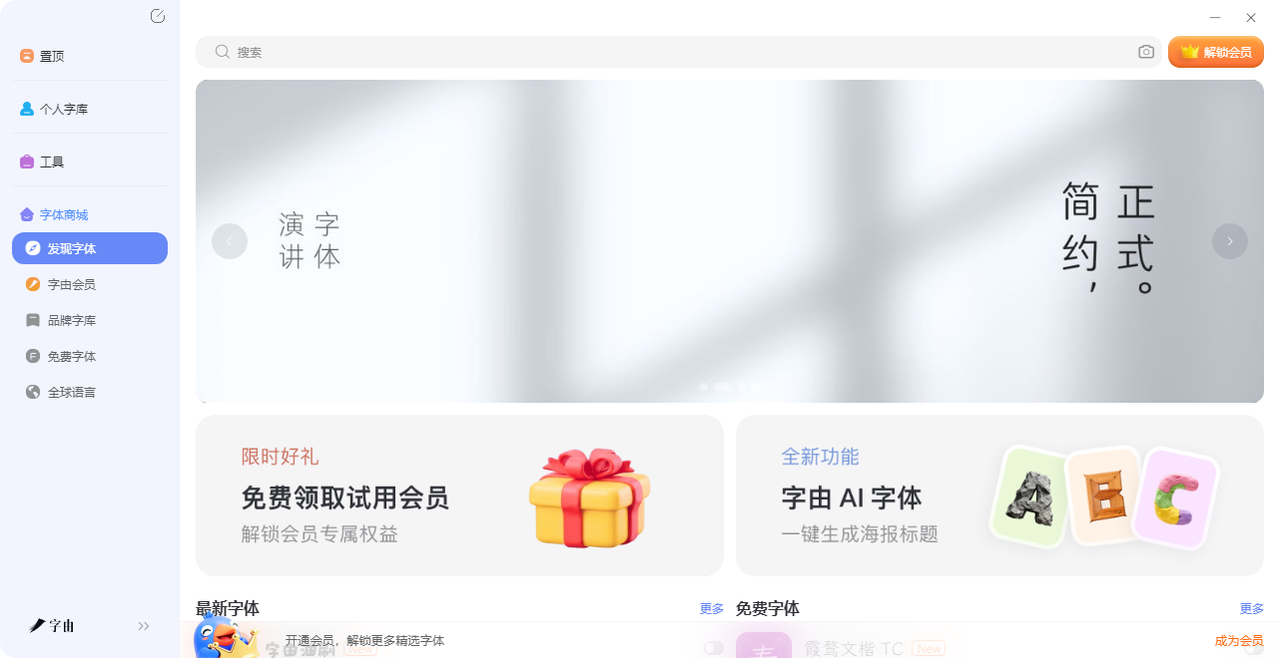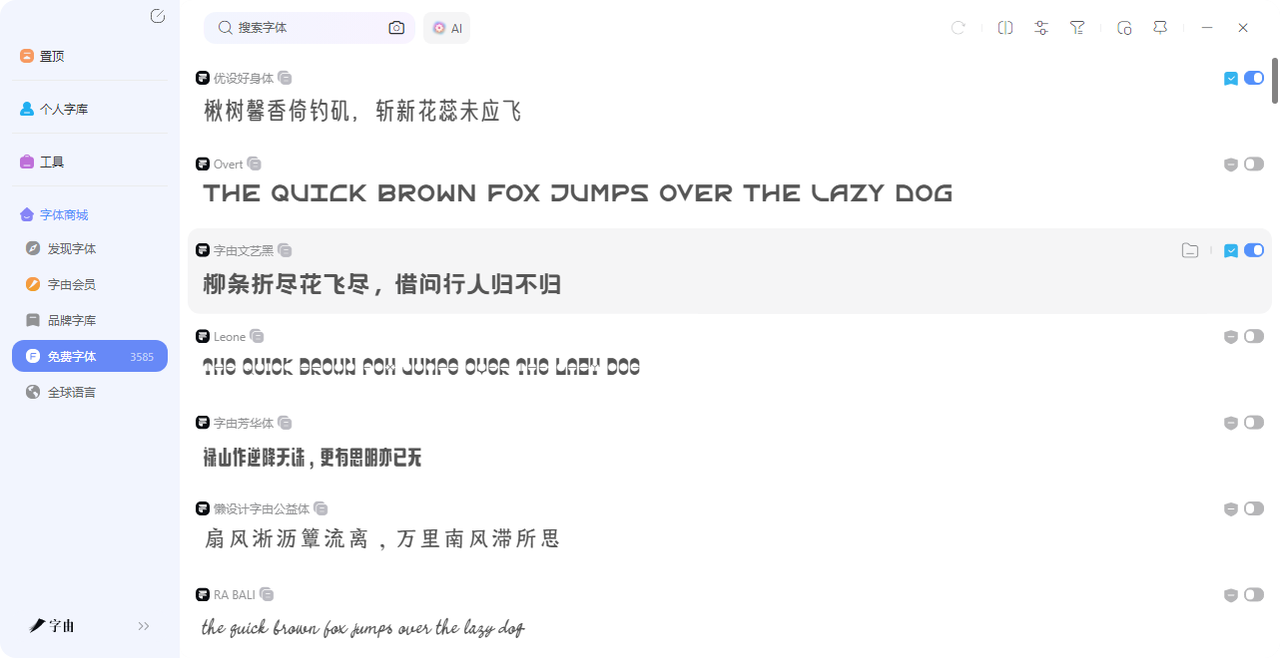
字体大师实测:字由的免费商用字体库和AI工具到底有多强?
如果说你在做设计,但是还没有听说过或者是还没有用到过字由,那简直是亏大了。它不仅是一个字体工具,不用下载安装字体文件,点一下就能直接在PS和Word里用,而且库里目前还有3000多款免费商用字体,还带了AI识字、AI字体生成这些非常实用的功能,完全能称得上“字体大师”,今天我会挨个把字由好用的地方都给你讲讲。
字由(hellofont.cn)是一个集字体库、字体管理、AI工具于一体的平台。隶属于上海驿创信息技术有限公司,2015年创立,核心口号是“让用户用字更自由”。目前聚集了超千万设计师、创意人才、运营人员等用户。
它有网页版和客户端两种形态。网页版可以浏览和预览字体,但要想真正把字体用到PS、AI里,得下载客户端。客户端才能实现“一键应用到设计软件”。
2、免费字体库
这是字由最核心的价值。关于免费商用字体的数量,不同渠道的数据略有差异,但都在一个量级。
官方在2026年初的版本更新中提到,平台收录了10500多款字体,其中免费商用字体已增加到3585款。这个体量在国内同类平台中属于第一梯队。更重要的是,这些字体都有第三方厂商的正版授权。每一款在详情页都会明确标注授权类型和商业使用权限,从源头降低版权风险。
具体到字体,热门的有这些:中文字体方面,黑体类有思源黑体、阿里巴巴普惠体、优设标题黑、字由文艺黑、鸿蒙黑体、钉钉进步体、站酷酷黑等;宋体类有思源宋体、思印宋等;楷体类有阿里妈妈东方楷体、江西拙楷等。英文免费商用字体则包括Playfair Display、Oswald Medium、Hanchan Serif、Poppins Bold等。其他热门款还有优设好身体、阿里妈妈东方大楷、抖音美好体等,全部支持免费商用。
3、实用AI工具
字由不是只有字体库。它内置了好几款AI工具,覆盖了字体识别、生成、配字等场景。
AI识字:上传图片,3-5秒识别字体
这功能解决了一个特别实际的痛点——看到一张海报上的字体很喜欢,但不知道叫什么。操作很简单:打开字由客户端或官网,进入「AI识字」功能页,把图片拖进去,系统3-5秒内自动分析并识别文字区域。然后返回匹配的字体结果,同时标注是否为免费商用字体及授权类型。如果你在PS或Figma里设计,可以直接点击激活字体,然后在软件里立即使用。
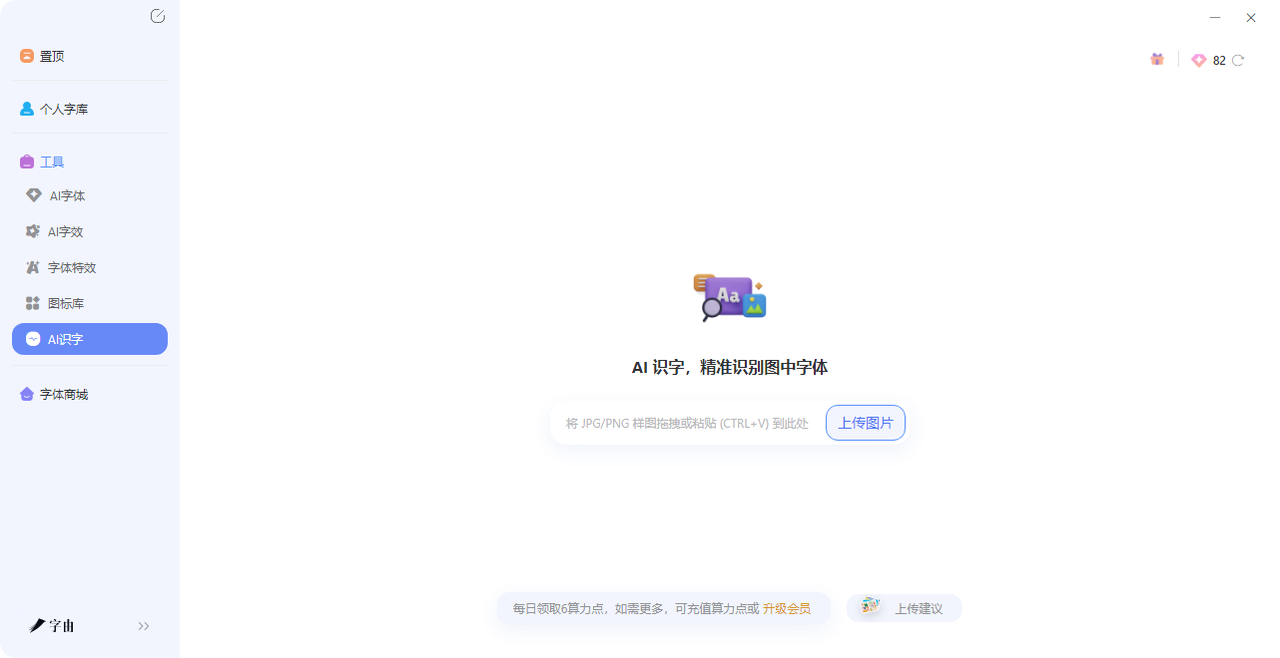
字由5.0版本还进一步升级了这项功能:AI会在识别后同步匹配库内的官方授权信息与商业使用权限,并提供相似字型选项。也就是说,哪怕识别出来的字体不在字由库里,系统也会给你推荐长得像的替代品。
AI字体:输入文字,选模板,几十秒生成艺术字图片
这功能适合不会PS又想出艺术字效果的人。操作分三步:打开字由的AI字体功能页,选模板(电商促销、国风、涂鸦、科技感等风格全覆盖),点“做同款”,输入想做的文字(比如“开业大吉”“春日上新”),点生成。生成时间大约6-7秒,和模板风格一致,笔画比例规整。生成后可以下载透明背景的PNG图,拖进海报直接用。
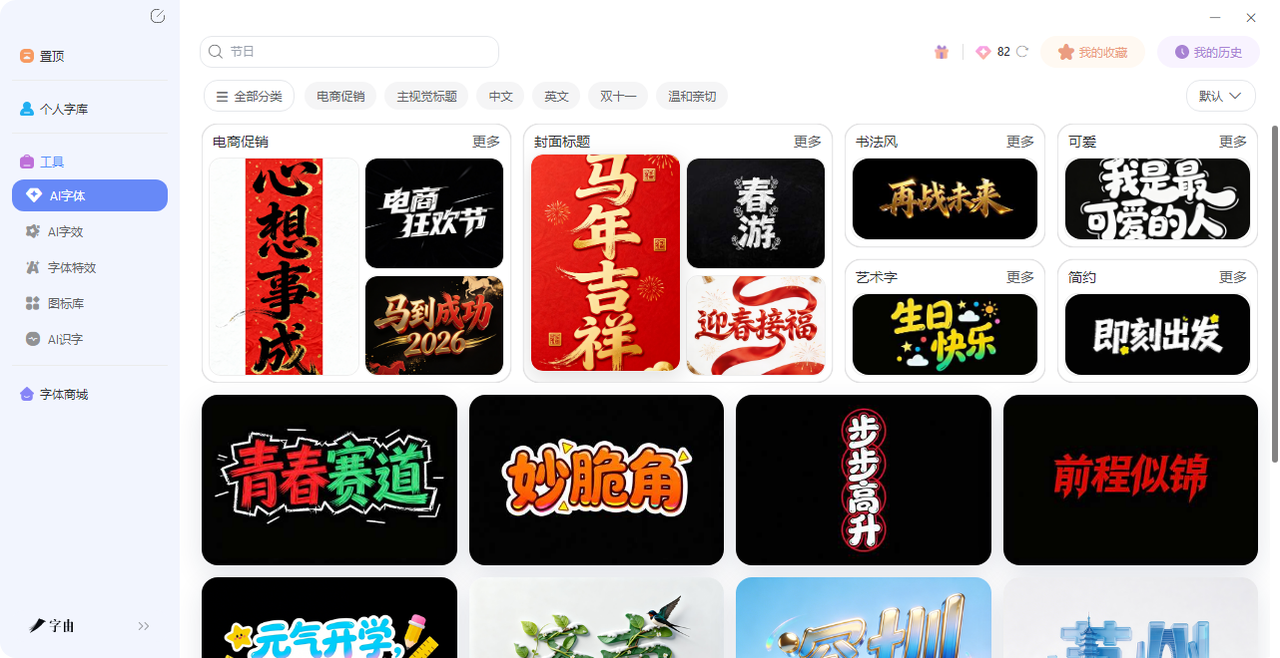
字由AI字体的定位是“将复杂留给自己,将简单留给用户”,通过预制高质量字体模板实现“输入即所得”。在4款国产AI字体工具的横向测评中,它在稳定性和易用性上表现最佳。缺点是完全不懂AI的新手也能顺畅使用,能保证质量。缺点是自定义自由度较低。
AI擦除:去水印修图,几秒搞定
上传一张带文字的图片,AI智能识别图中所有文字,你想去掉哪句就选哪句,擦除后背景自动修复,看不出痕迹。做海报去水印、改文案修图,几秒钟搞定。
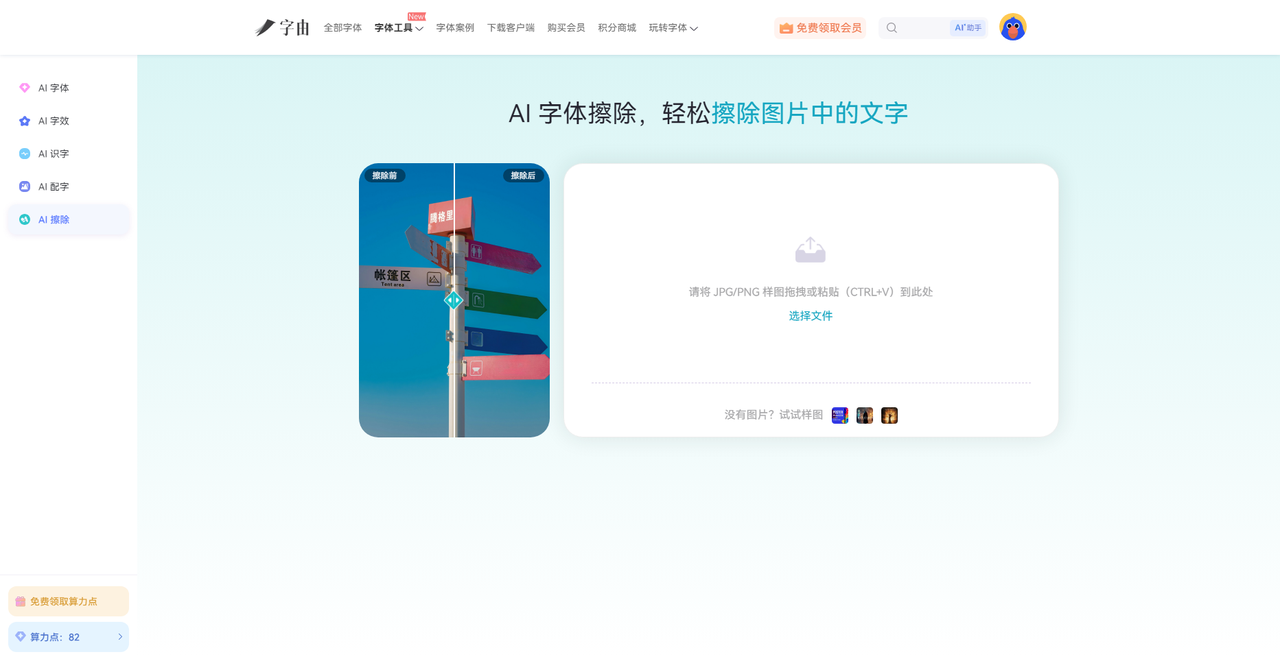
AI配字:根据图片推荐字体
上传图片后,AI自动识别图中的元素(风景、人物还是产品),然后从海量字体库中推荐最适合这张图片的字体。还可以自定义文字内容和样式,一键生成效果图。
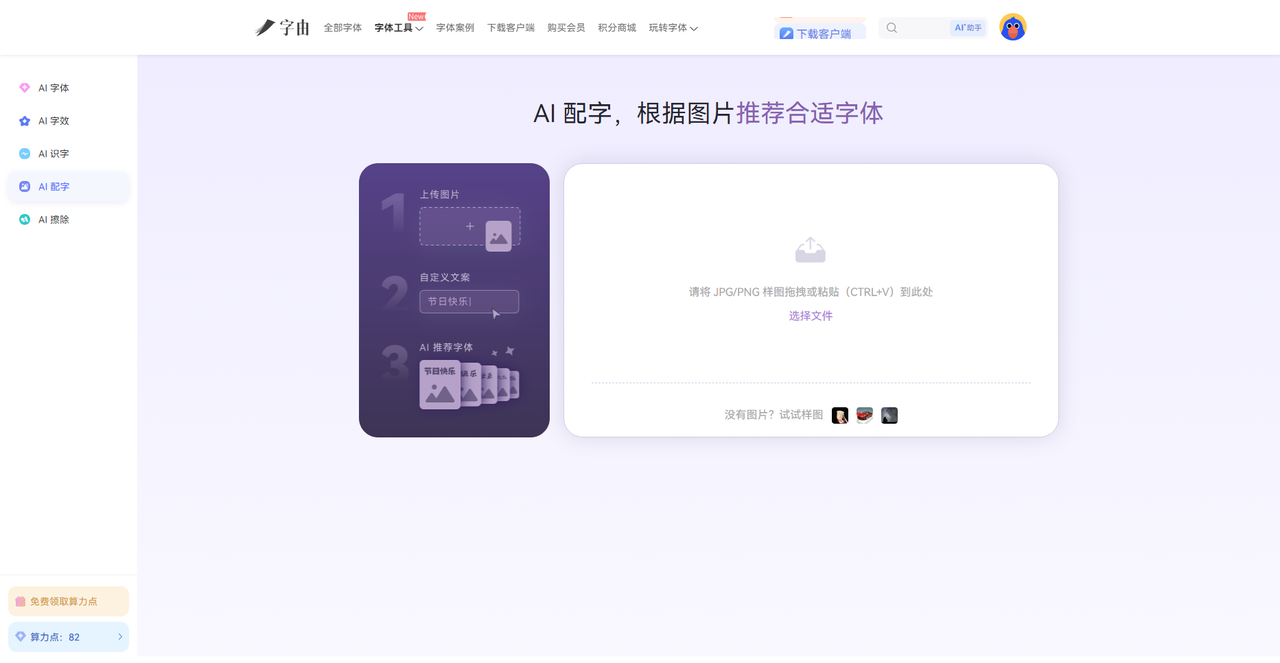
AI助手:智能对话,字体顾问
字由5.0还新增了AI助手,是一个智能对话式的私人字体顾问。可以问它字体相关的问题,它会深度思考后给出精准解答。
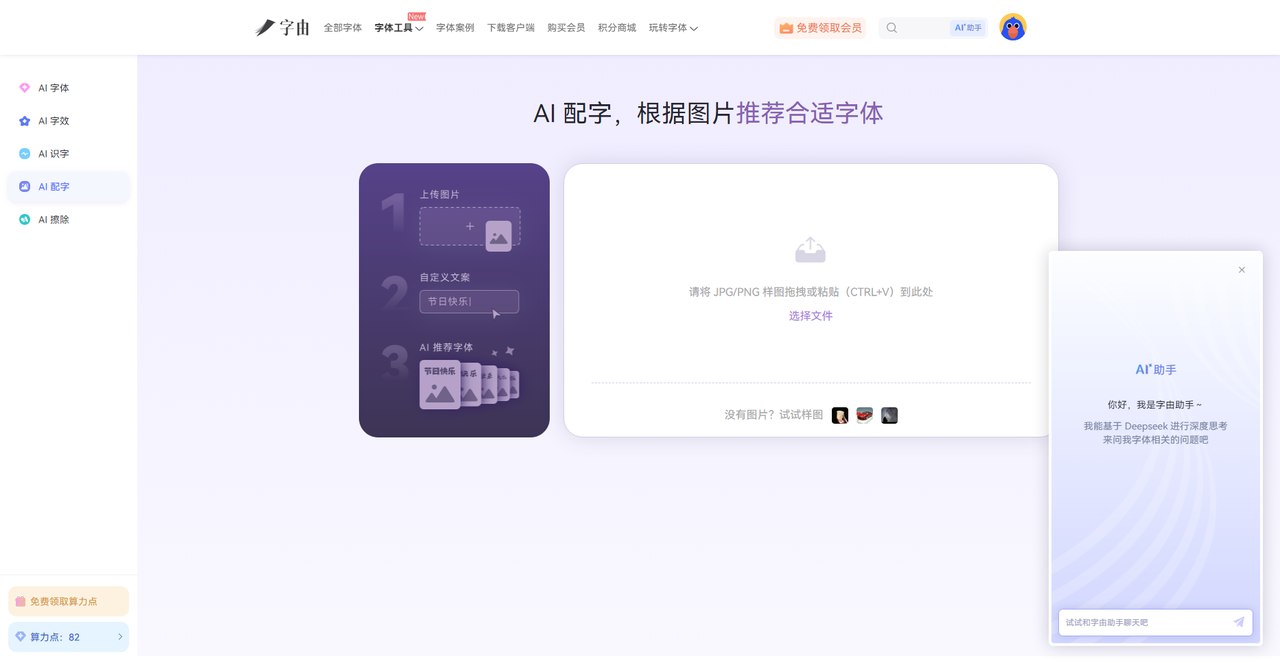
4、一键激活字体
字由和其他字体网站最大的区别是“云端用字”模式——不需要把字体文件下载到本地,只需要安装客户端,在PS、AI等软件中选中文字,再在客户端激活对应字体,即可直接应用。
具体操作:打开设计软件(比如PS),新建文件,用文字工具输入一段文字,选中这个文字图层。然后在字由客户端激活想要用的字体,就能看到字体成功替换到设计软件里。
字由客户端支持在PS、AI、ID、XD、Figma、Sketch、CDR等设计软件中一键应用字体,省去了查找、下载、安装的麻烦。
5、个人云字库
字由的个人云字库本质是一个云端字体管理工具,核心价值在于:把你常用的字体存到云端,换设备登录同一账号后自动同步,不用重复筛选和激活。 字由官方明确提到,它的设计初衷是解决“电脑坏了、U盘丢了”带来的字体丢失问题,只要账号还在,字体就一定在。
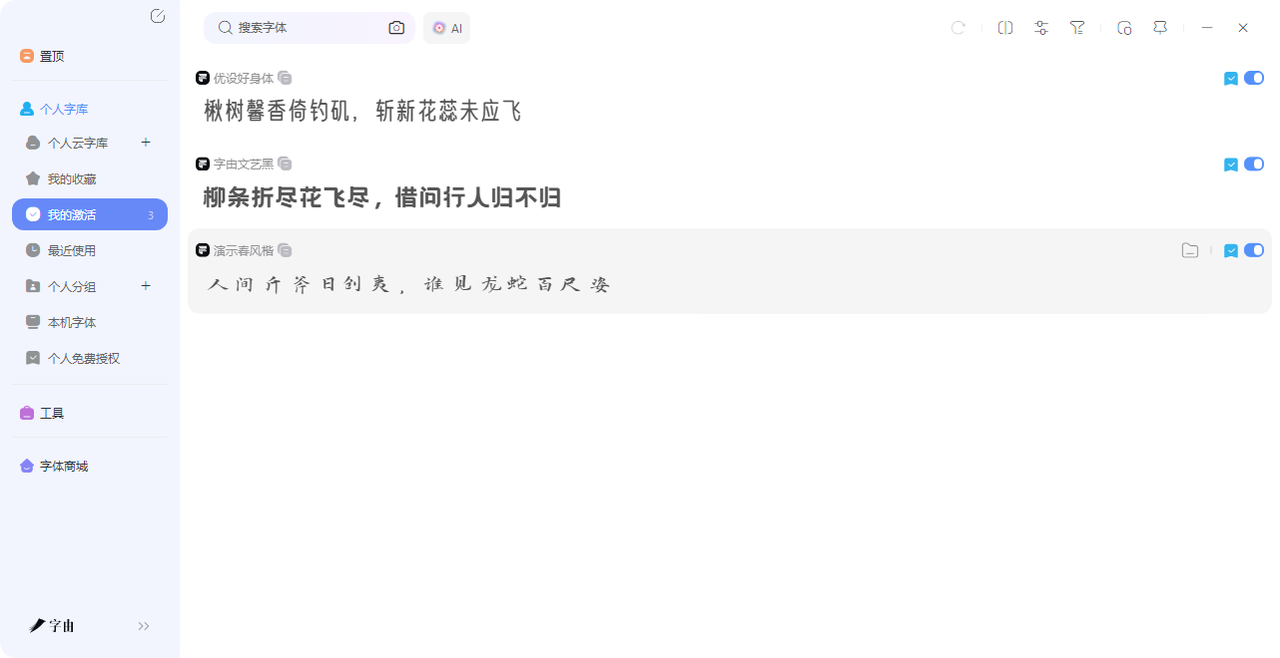
但是有一点需要注意,激活数量不宜过多。激活字体数量过大会导致客户端响应变慢甚至卡顿,不提供一键激活全部字体的按钮,建议只激活当前要用的字体,而且上传至云字库的本地字体,版权归属由上传者自行负责,字由不会替你审核。
如果你需要大量免费商用字体,不想一个个去网站下载、解压、安装、重启软件,字由值得装。3000+款免费商用字体,涵盖了日常设计所需的主流风格,版权标注清楚,不用担心侵权。如果你需要识别图片里的字体,或者想快速出艺术字效果,字由的AI工具够用。AI识字3-5秒出结果,AI字体几十秒出图,而且每日免费算力足够轻度使用。当然,字由不是完美的。AI字体的自由度确实有限,没办法像手动调那样精确控制每个细节。但对于大多数日常设计场景,模板库的丰富程度已经足够了。